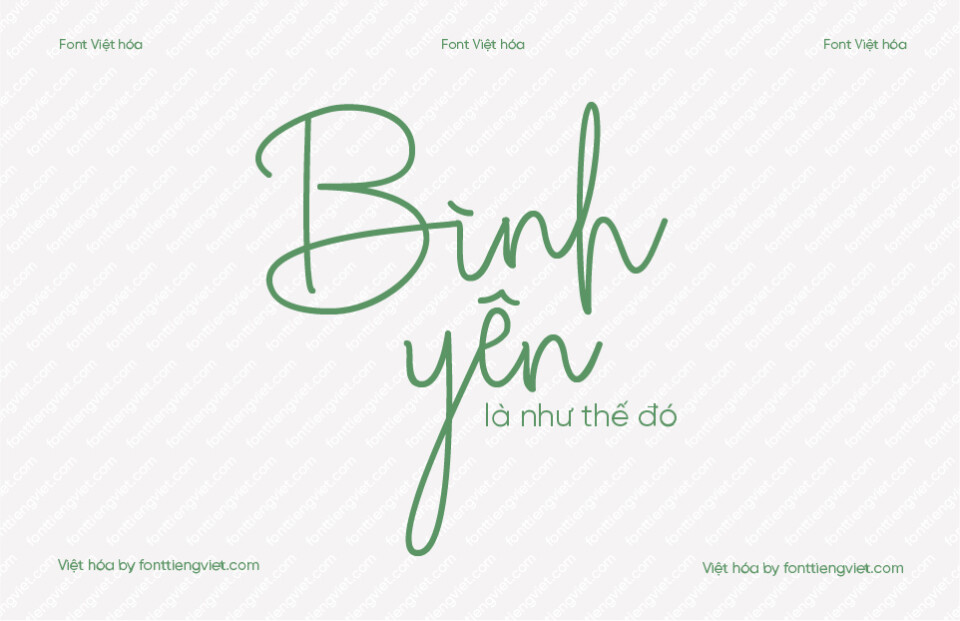
Giới thiệu về Font Việt hóa 1FTV VIP Broetown Signature
Trong thế giới thiết kế đồ họa hiện đại, việc lựa chọn một Font Chữ phù hợp đóng vai trò quyết định đến tính thẩm mỹ của sản phẩm. Font Việt hóa 1FTV VIP Broetown Signature là một bộ phông chữ viết tay dạng chữ ký đầy ấn tượng, mang phong cách thanh lịch và phóng khoáng. Được đội ngũ 1FTV tinh chỉnh và việt hóa kỹ lưỡng, bộ font này giúp người dùng dễ dàng thể hiện các nội dung tiếng Việt mà không lo lỗi dấu hay khoảng cách chữ. Đây là lựa chọn hoàn hảo cho các bạn học sinh, sinh viên và giáo viên muốn tạo ra những bài thuyết trình hay tài liệu học tập có dấu ấn cá nhân độc đáo.
Đặc điểm nổi bật của bộ Font Việt hóa 1FTV VIP Broetown Signature
Phong cách thiết kế chữ ký tinh tế
Font Việt hóa 1FTV VIP Broetown Signature sở hữu những đường nét mảnh mai nhưng vô cùng chắc chắn, mô phỏng chân thực nét bút ký tay tự nhiên. Các ký tự được liên kết với nhau một cách mượt mà, tạo nên tổng thể hài hòa và chuyên nghiệp. Điều này giúp bộ font cực kỳ phù hợp cho các dự án thiết kế logo, thiệp mời, bìa sách hoặc làm chữ ký số trên các văn bản điện tử.
Khả năng ứng dụng đa dạng trong giáo dục và đời sống
Với sự phát triển của công nghệ, việc sử dụng Font Việt hóa 1FTV VIP Broetown Signature trong môi trường học đường ngày càng phổ biến. Thầy cô có thể dùng font này để thiết kế lời tựa cho giáo án, trong khi học sinh dùng để trang trí các poster sự kiện trường học. Tính tương thích cao với các phần mềm phổ biến như Word, Photoshop hay Canva giúp người dùng thỏa sức sáng tạo mà không gặp bất kỳ rào cản kỹ thuật nào.